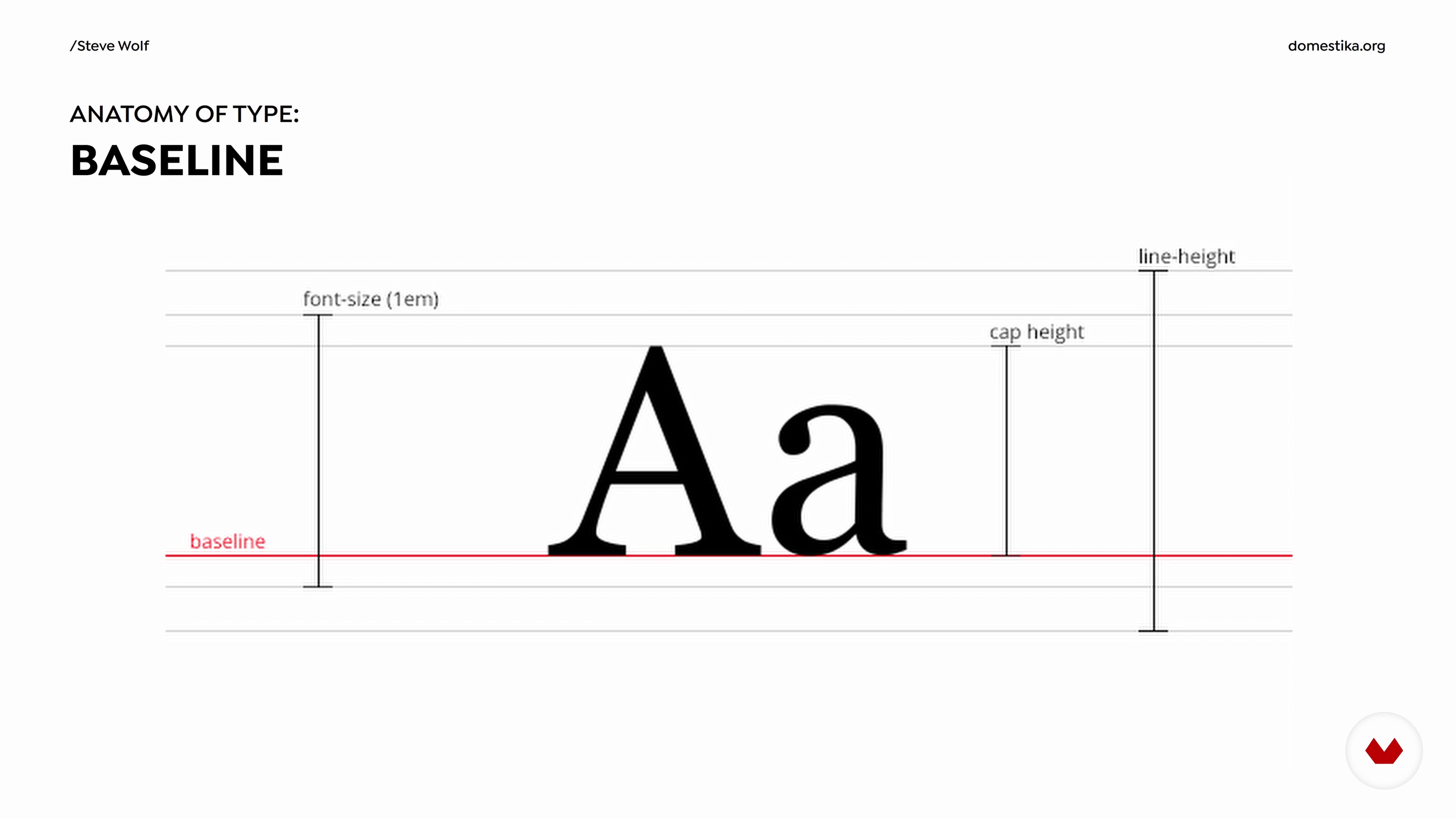
Les concepts de base et l'anatomie de la conception de typographie
À propos de la leçon : Les concepts de base et l'anatomie de la conception de typographie
“Maintenant, je vais passer en revue les concepts de base et l'anatomie de la conception typographique.”
Dans cette leçon, Steve Wolf aborde le sujet : Les concepts de base et l'anatomie de la conception de typographie, qui fait partie du cours Domestika en ligne : Conception de logos : définissez l'identité d'une marque. Apprenez à créer un logo intemporel pour une marque ou un produit en explorant la typographie et le graphisme.
“Les concepts de base et l'anatomie de la conception de typographie Maintenant que vous connaissez les principes d'un logotype réussi, dans cette leçon, nous passerons en revue les concepts de base et l'anatomie de la conception de la typographie. Comprendre les formes de lettres est un processus sans fin que nous devrions continuer à apprendre et à évoluer tout au long de nos carrières de designers. La typographie est la base de toute conception de logotype, il est donc important de comprendre son fonctionnement avant de le maîtriser, afin que nous puissions créer nous-mêmes des logos réuss...”